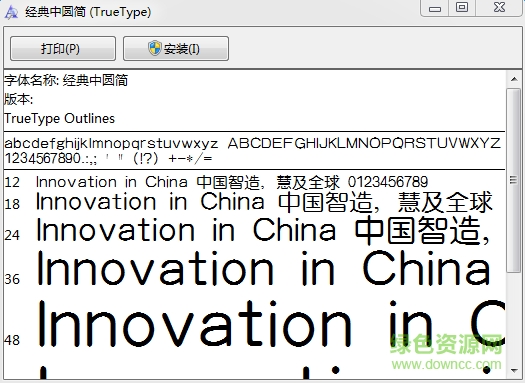
經(jīng)典中圓簡(jiǎn)體
經(jīng)典中圓簡(jiǎn)是經(jīng)典字庫(kù)中一款很實(shí)用的電腦簡(jiǎn)體字體,這款字體寫(xiě)出來(lái)的字是很整齊的,而且很好看,很秀氣,可以用于很多方面,比如寫(xiě)作、題字題詞等都很不錯(cuò),有需要的朋友可以來(lái)綠色資源網(wǎng)下載。